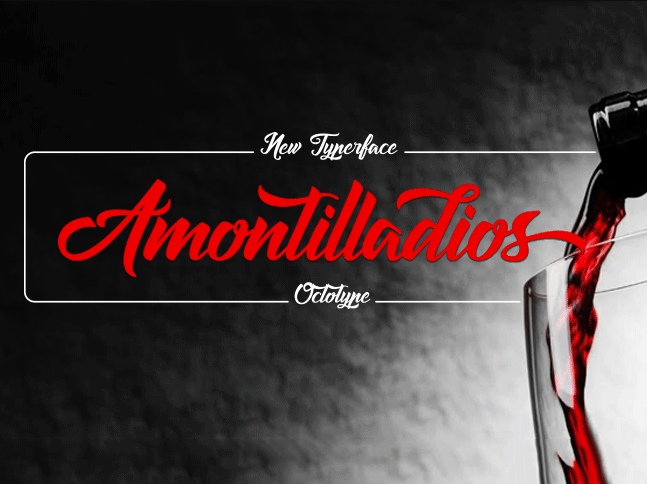
A Amontilladios Typeface é uma tipografia script que combina a elegância suavemente fluida com a personalidade vivaz do estilo. Esta fonte é ideal para designers amantes de texturas, capazes de criar mensagens emocionantes e visualmente atraentes, seja em design editorial, mídia gráfica ou criação web. Com sua estrutura delicada e movimentos suaves que a fazem percorrer como um rio subterrâneo, a Amontilladios Typeface oferece uma experiência de leitura única e envolvente. A Octotype é conhecida por criar fontes com personalidade, cada caractere em Amontilladios parece ter sido formado em delicadas gotas que descem do céu azul através da água suavemente esculpida das letras. Esta fonte permite que designers criem texturas e atmosferas únicas, trazendo vida à qualquer projeto, tornando-a uma escolha imprescindível para quem busca um toque de elegância e sofisticação em seus trabalhos.
Designer: Octotype